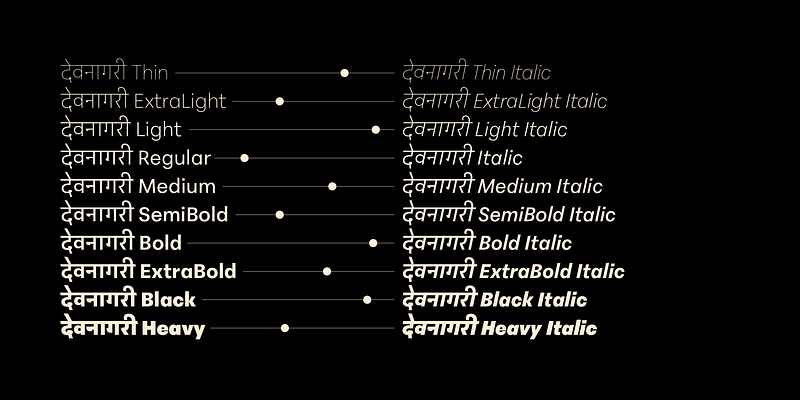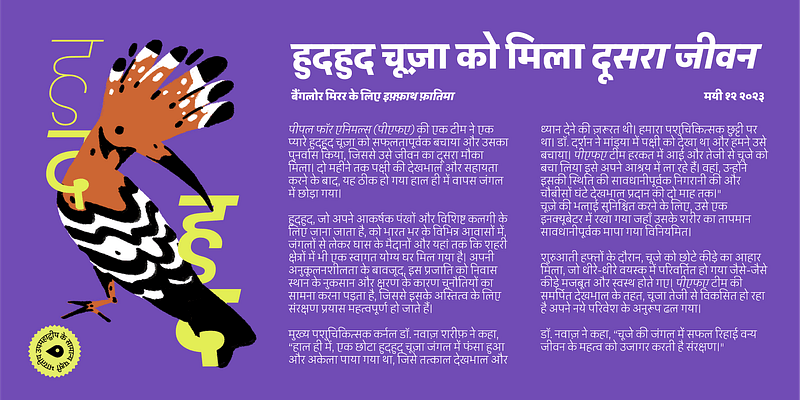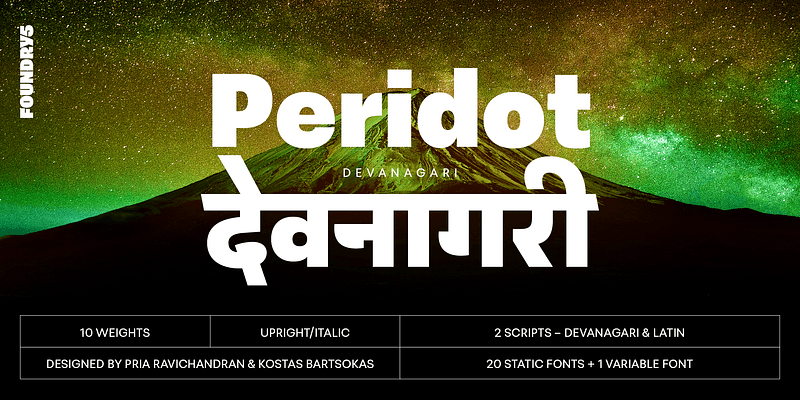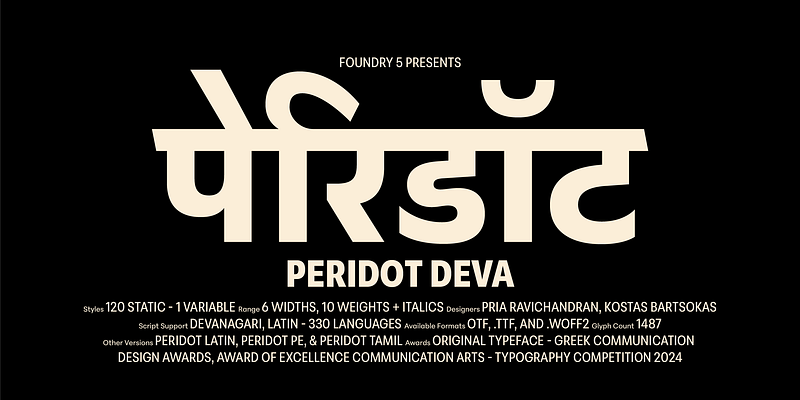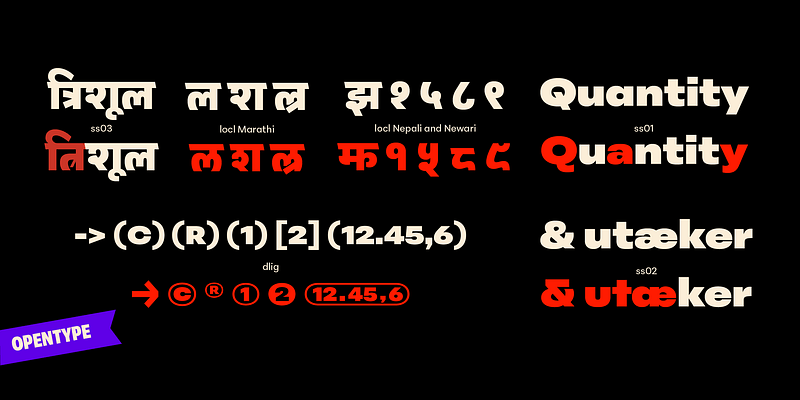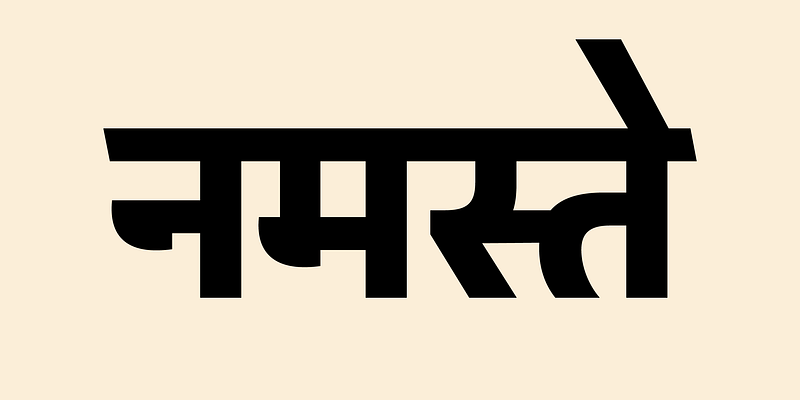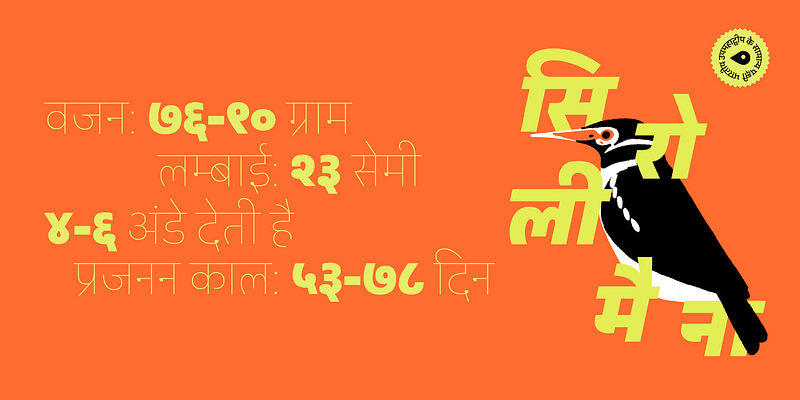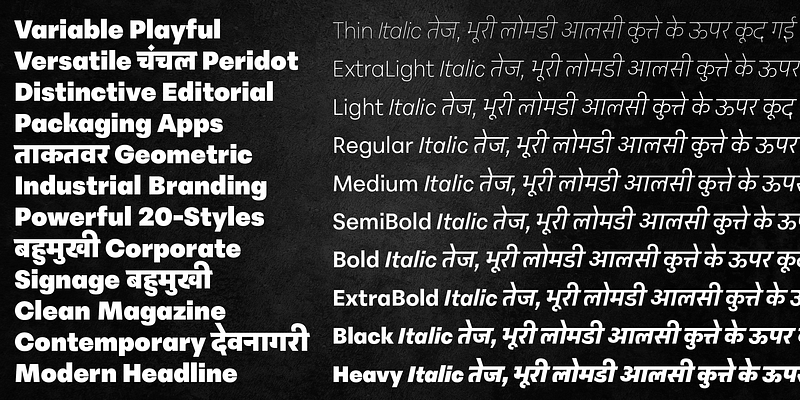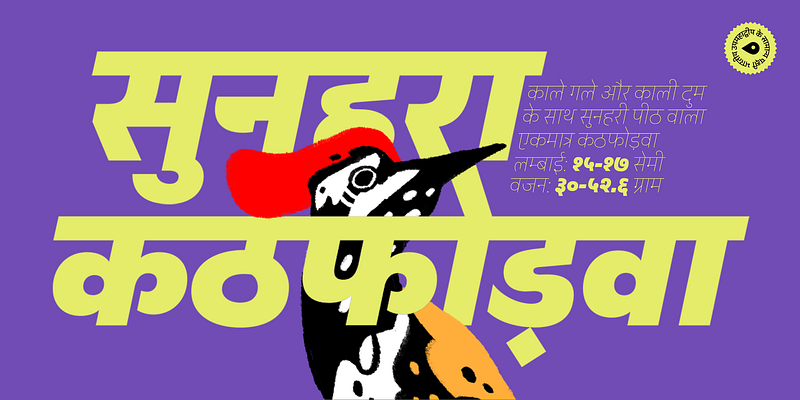
Peridot은 단순한 서체가 아닙니다. 이는 Foundry5가 열정과 정밀함으로 제작한 다면적인 산세리프체 시스템입니다. 오랜 시간에 걸쳐 공들여 개발하고 모든 미세한 세부 사항에 집중한 이 서체는 6개 너비의 이탤릭체와 매우 다양한 가변 형식을 갖춘 고품질 10개 굵기 계열을 자랑합니다. 개성이 넘치는 Peridot는 다양한 스타일 변형을 실험해 보고 창의적인 비전에 완벽하게 맞게 타이포그래피 톤을 조정할 수 있도록 초대합니다. Peridot의 다양한 너비와 스타일은 역동적인 타이포그래피 도구 상자를 제공하여 가장 혁신적인 디자이너에게도 영감을 주고 마음을 사로잡을 준비가 되어 있습니다.